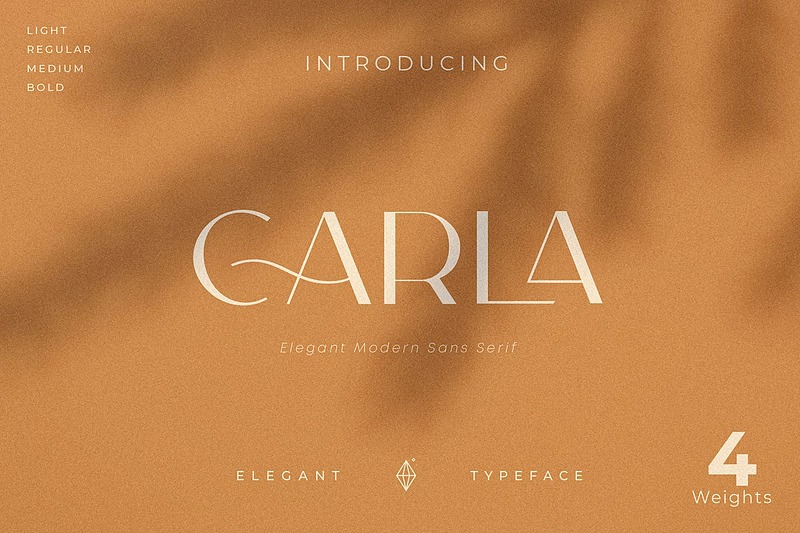
فونت انگلیسی الگانت مدرن فمینین (Carla)
معرفی فونت کارلا
کارلا سنس یک فونت مدرن مینیمالیستی وینتیج استایل با لیگچرهای زیبا، چندین گلیف آلترنیتیو ویژه، اورنامنت و پشتیبانی چندزبانه است. این یک فونت همه‌کاره است که در اندازه‌های بزرگ و کوچک عالی عمل می‌کند.
کارلا برای پروژه‌های برندینگ پرفکت است، طراحی لوگو، برندسازی پوشاک، بسته‌بندی محصول، سرصفحه‌های مجلات، یا صرفاً به‌عنوان پوشش متنی شیک برای هر تصویر پس‌زمینه‌ای مناسب است.
• 4 وزن فونت
• همه کاراکترها کپیتال
• استایلیستیک آلترنیت‌ها و لیگچرها
• اعداد و علائم نگارشی
• کاراکترهای اکسنت
• چندین زبان پشتیبانی می‌شود
• طبقه‌بندی: سنس سریف
• فاصله‌گذاری: نرمال
• اندازه بهینه: هر اندازه‌ای